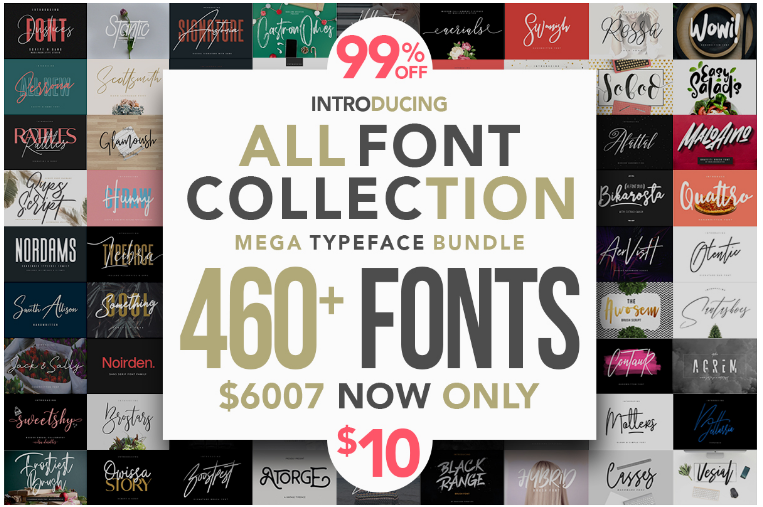
[Creativefabrica] All Fonts Collection - Mega Typeface Bundle (Maulana Creative)
All Fonts Collection - Mega Typeface Bundle - это невероятный набор из +460 шрифтов, включающий 459 различных продуктов.
Придайте своему дизайну аутентичность ручной работы с помощью этого набора, который идеально подходит для подписи, канцелярских принадлежностей, логотипов, типографских цитат, обложек журналов и книг.
Этот чудовищный пакет включает в себя шрифты премиум-класса!
В этом пакете представлен широкий спектр стилей шрифтов: подпись, каллиграфия, шрифт, шрифт кисти, гранж, шрифт с засечками, шрифт без засечек, шрифт логотипа, рукописный шрифт, ручной шрифт, Хэллоуин, комикс, Рождество и многое другое!